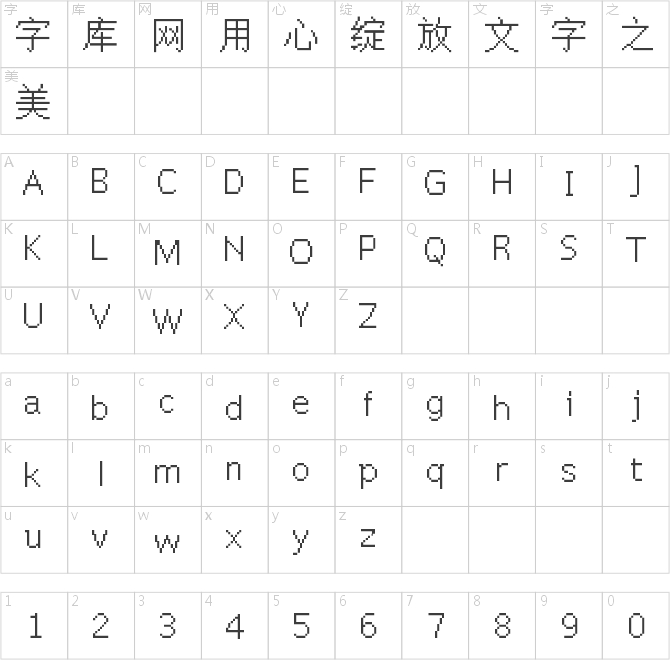
字体名称: 文泉驿点阵宋
文泉驿点阵宋
文泉驿点阵宋介绍
文泉驿点阵宋体是一个”自由中文字体”。该字体包含了所有常用简体中文、繁体中文,日文及韩文所需要的汉字(最新版本包含超过27842个汉字,完整覆盖GB2312/Big5/GBK/GB18030标准字符集)。该字体同时还包含了英文、日文、韩文和其他多种语言符号。该点阵字体包含五个屏幕常用字号(9pt-12pt),逾21万汉字点阵,这些点阵都经过参与者和组织者的精心设计和调整,手工优化后的汉字点阵显示清晰锐利,特别易于屏幕阅读使用。
此为娱乐部以文泉驿点阵宋体 v1.0.0-RC1 的 PCF 字体制作的 TTF 版字体。希望可以给中文的点阵字体和像素字体增加一个新的选择。